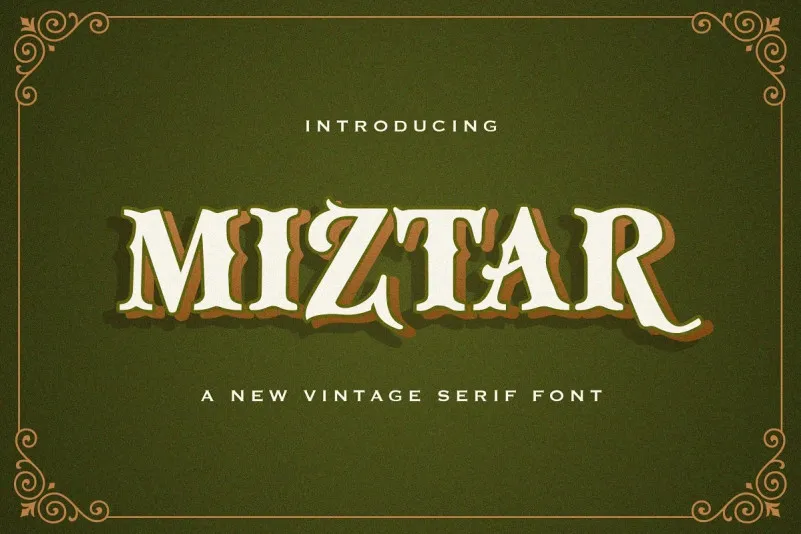
Miztar Blackletter Font – Download Grátis
A Miztar Blackletter Font é uma exuberante revisão do tipógrafo clássico Victoriano inspirado nos selos e sinais de loja dos finais do século XIX e início do século XX. Esse tipo de impressão, ainda hoje tão caro e sofisticado, tem um apelo nostálgico que é perfeito para aqueles projetos que buscam uma atmosfera vintage única. Inspirada nas características elegantes e intricadas dos anos 1800 aos 1900, a Miztar Blackletter traz um respiro de frescura moderno para esse legado clássico, mantendo o seu encanto e força distintiva. Seja em materiais impressos ou digitalizados, esta fonte vai destacar-se em uma ampla gama de contextos, sejam eles rótulos de embalagens sofisticadas, selos de loja, gráficos de eventos históricos ou qualquer outro design que busque uma atmosfera vintage atemporal.